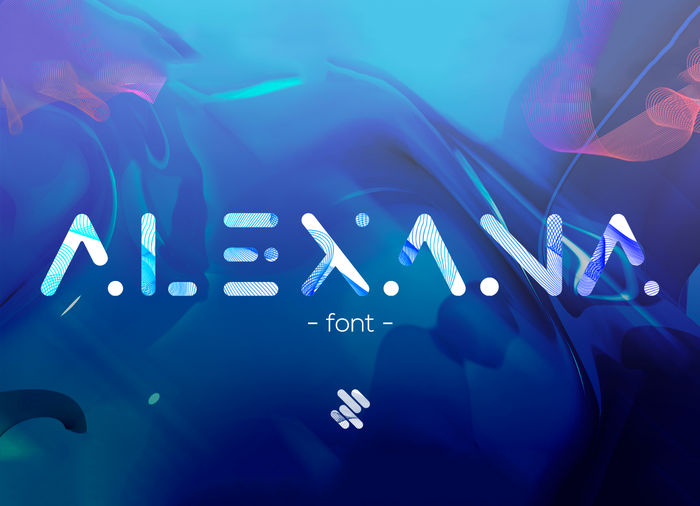
Alexana Display Font
Introduzimos a Alexana Display Font! A fonte foi criada pelo designer Mark Mora. Esta é uma bela fonte de exibição projetada para simplificar a criação de logotipos e headlines. Com sua grandeza, força e beleza, a Alexana se destaca como um tipo de fonte perfeito para projetos minimalistas. Através da Alexana, Mark Mora compartilhou seu talento em criar uma tipografia visualmente atraente, ideal para uso em logotipos, headlines e citações. Composto por traços robustos e elegantes, o Alexana é perfeito para quem busca um estilo moderno e forte na sua identidade de marca ou design gráfico. Seja você um estilista minimalista ou uma empresa que procura personalizar seu logotipo com sofisticação, a Alexana Display Font certamente se encaixa em sua necessidade.